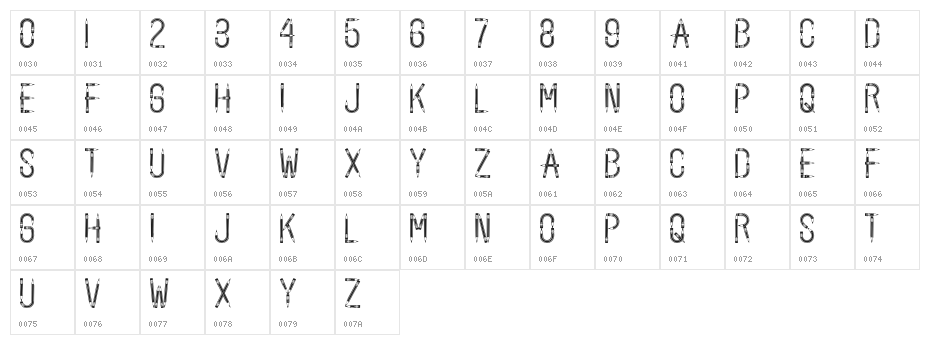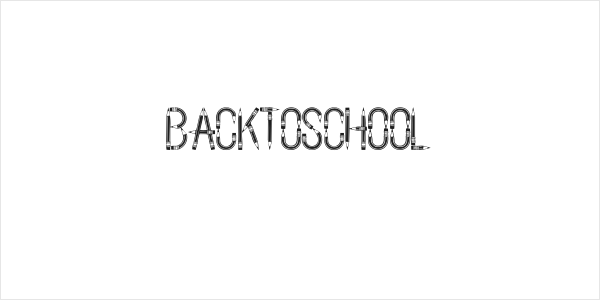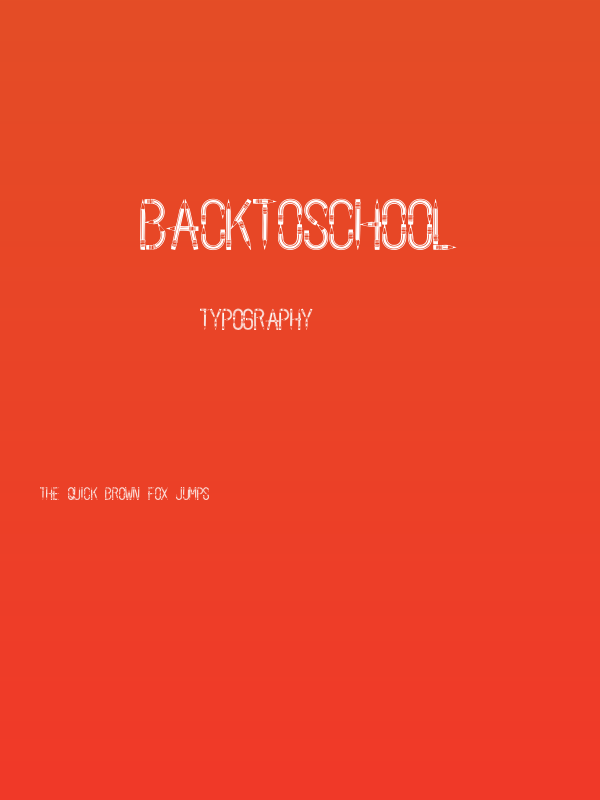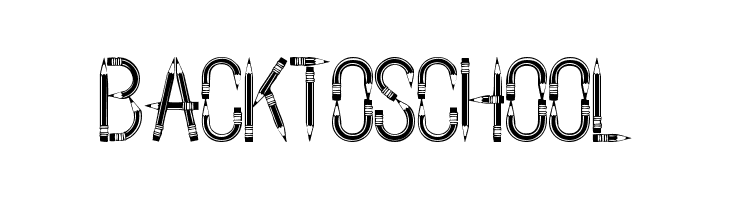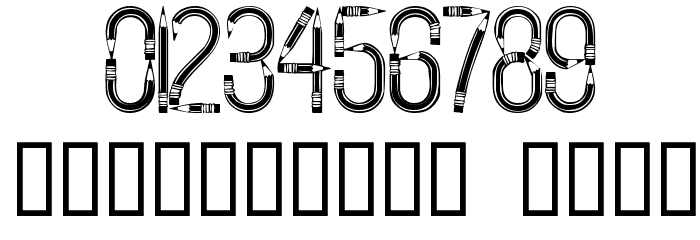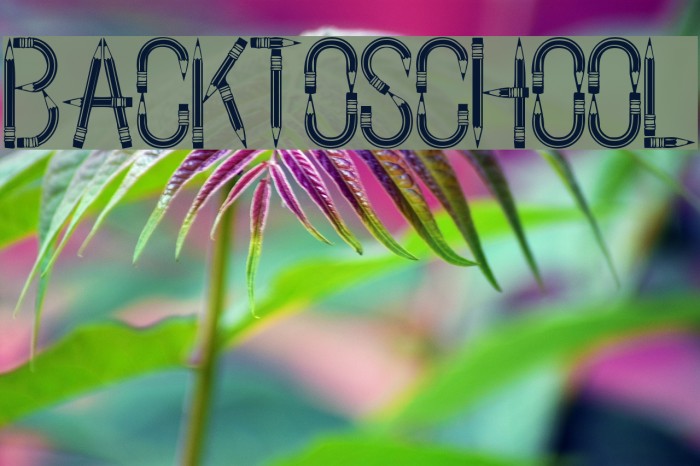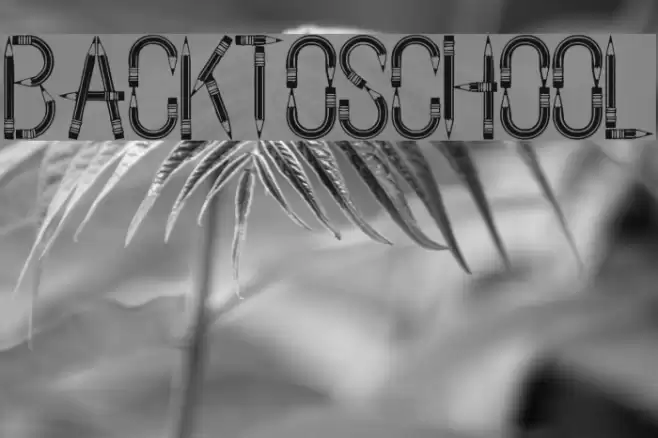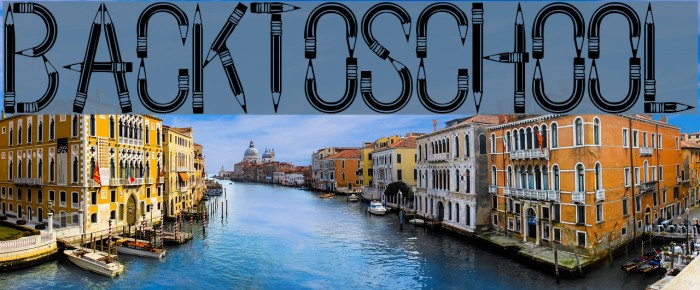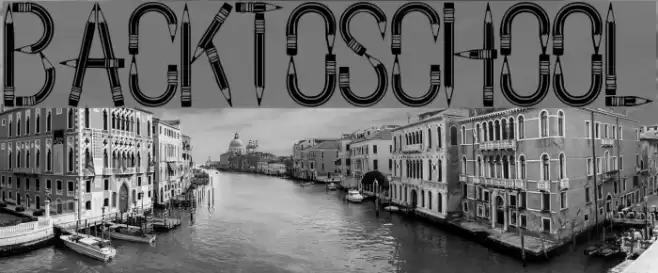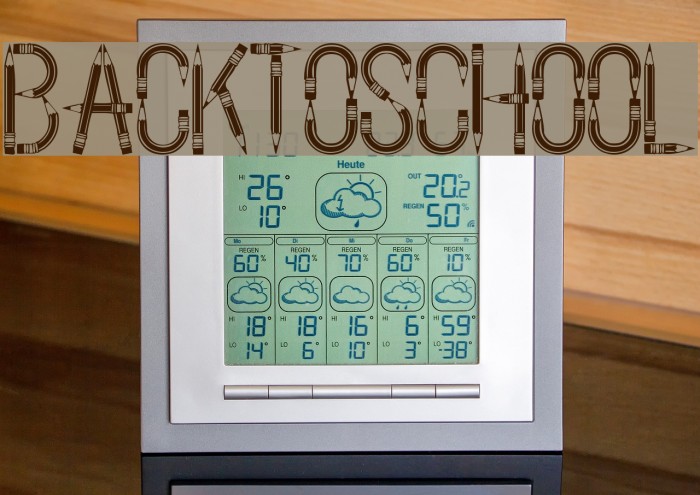
BackToSchool Font
✎ Decorative
| الفئات | Decorative |
| النمط العام | Playful, Educational |
| مشاريع مقترحة | Ideal for educational posters, school event invitations, children's book covers, and classroom decorations. |